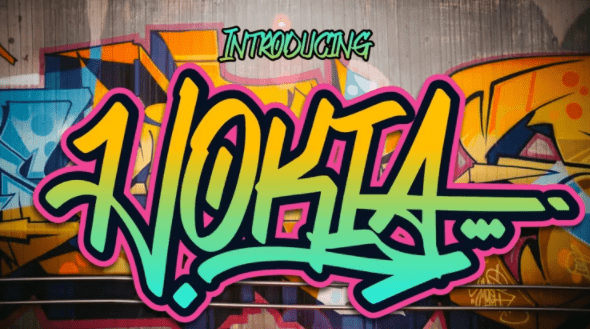
Hokia идеально подходит для упаковки продукции, брендингового проекта, мегажурнала, социальных сетей, свадьбы или просто используется для выражения слов над фоном.